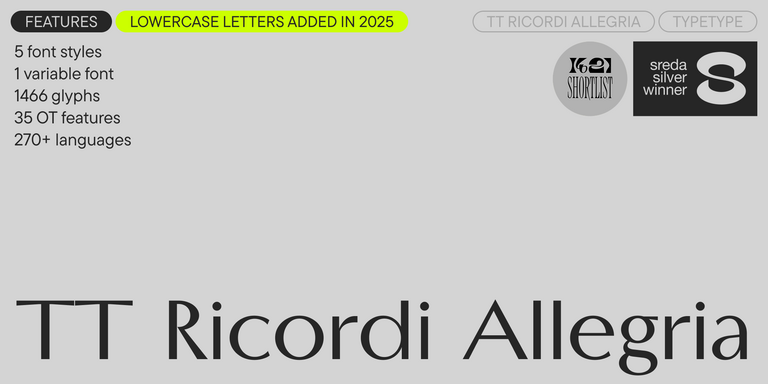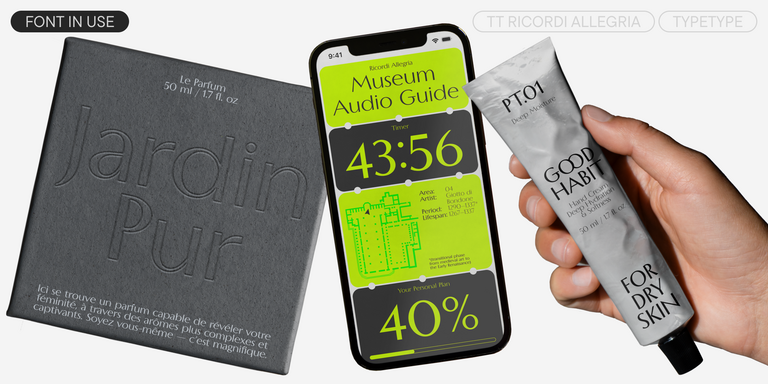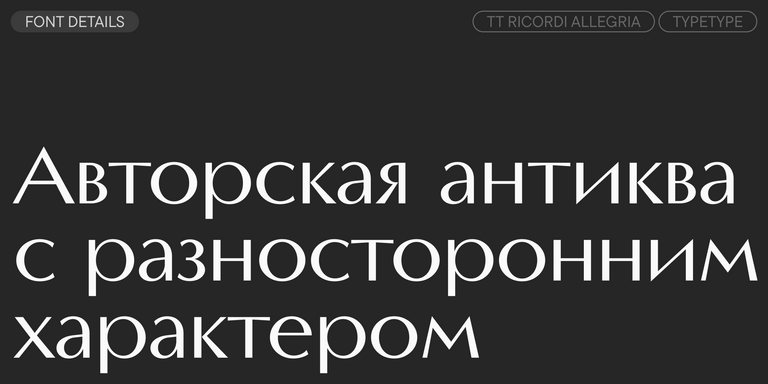
TT Bells сочетает в себе элегантную мягкость антиквы с непростым и дерзким характером, который выражается в прямых срезах и клинообразных засечках. В основе шрифта лежит ширококонечное перо, характерное для старостильных шрифтов, создающее эти атмосферные срезы и засечки.
TT Ricordi Allegria — современная ленточная антиква, отличительные особенности которой, гиперболизированная разноширинность в пропорциях, контраст между штрихами, клиновидные окончания штрихов и отсутствие традиционных засечек.
TT Drugs — ленточная антиква: это шрифт без засечек, но с выраженным контрастом.
TT Tricks — современная текстовая антиква, дизайн которой отсылает к стилю переходных антикв. Это шрифт со спокойным, элегантным и в меру строгим характером.
TT Geekette — вариативная антиква с дружелюбным характером. Мы ушли от упрощений сухой геометрии и поэкспериментировали с плавностью, мягкостью и пластичностью форм. А чтобы шрифт стал чуть более стильным и серьёзным, мы сделали его моноширинным.
TT Alientz является вариативным шрифтом, который позволяет пользователю совершить визуальное путешествие от лаконичного инопланетного гротеска к сверх акцидентной и очень колючей антикве.